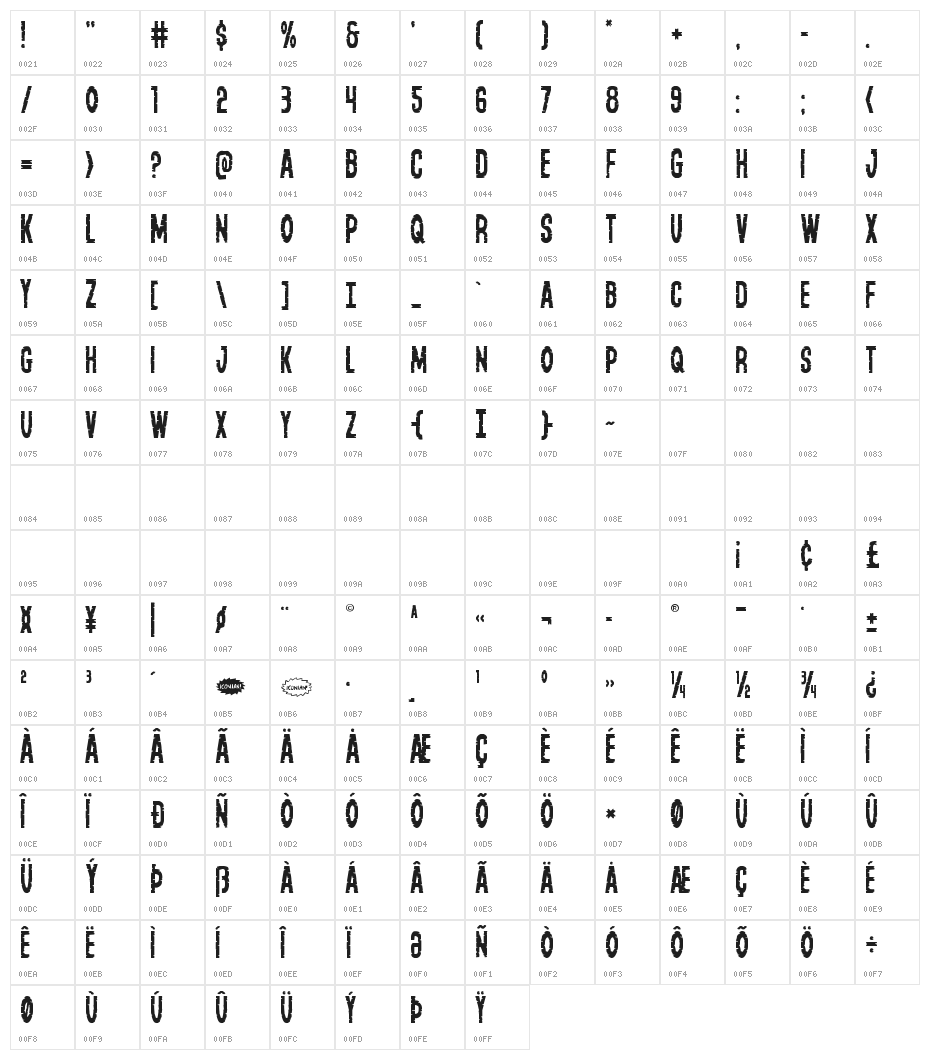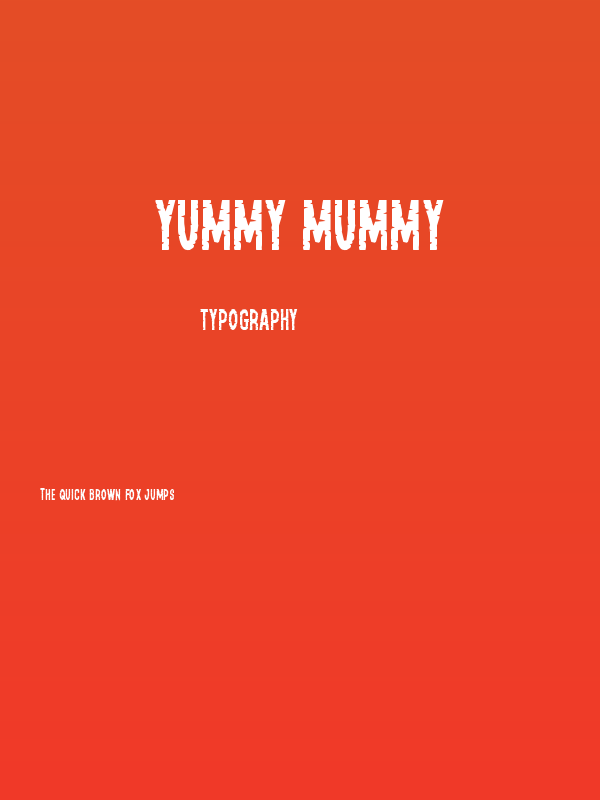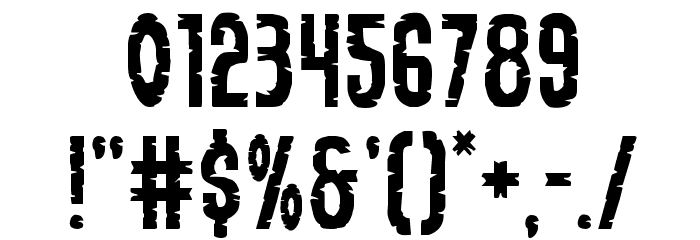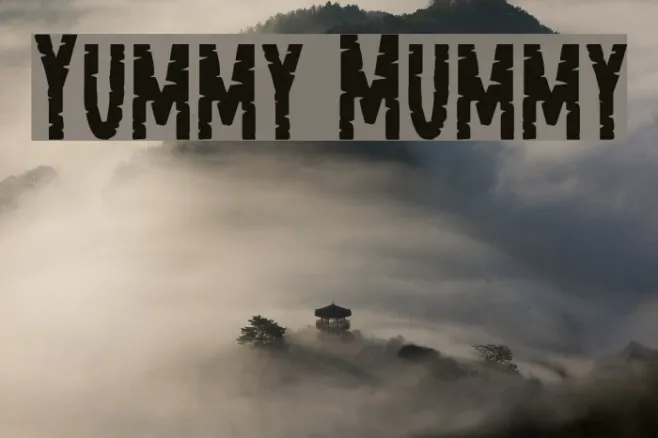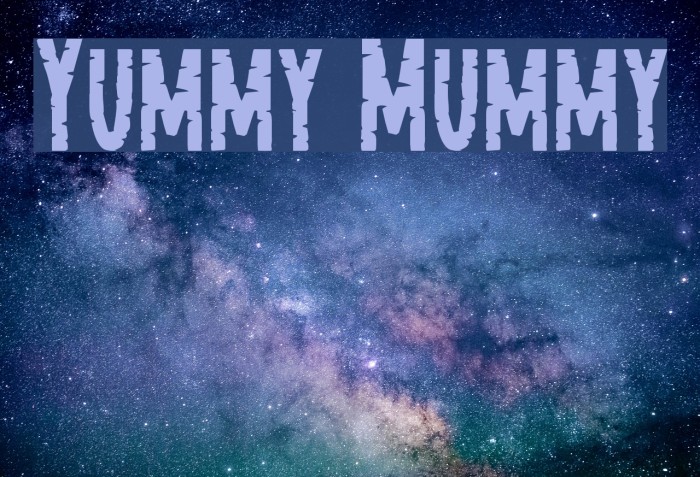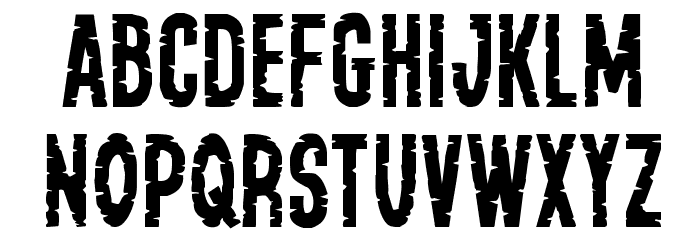
Yummy Mummy Font
| Estilo general | Vintage |
| Proyectos propuestos | Perfect for posters, album covers, branding for rustic or vintage-themed products, and any design needing a bold, eye-catching typeface. |